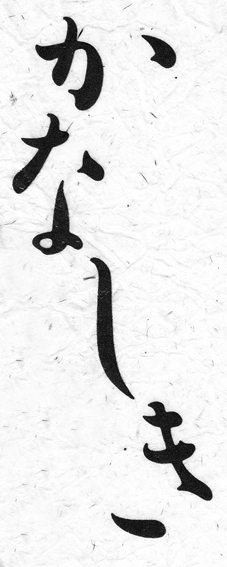
良寛
タイトルを聞くからにいかにも率直で脱力したエッセイ集である。
薄墨紙を思わせるグレーの表紙。その題字につかわれていた朱色の文字に、目が釘づけになった。
この本のことはなぜかいまでも覚えているのだが、改めて考えてみれば、かなの部分は「へ」と「な」の二つしかない、ということに気づいて愕然としてしまう。
その存在感は、きっと、不可思議な歪みのせいだ。
一見不揃いのようで、みる者を惑わせる微妙なずれ。そのくせじっと眺めていると、哀しげな表情から温もりが伝わってきて心が安らぐ。
このあやしくておもしろいかな書体は〈良寛〉という名前で、ほんとうに、あの良寛の筆跡からつくられたものだという。
幼少のころから和歌に親しみ、優れた詩人であった禅僧の良寛だが、書家としても有名で、古い名筆と呼ばれる書が残っている。
私にとって、良寛は、手毬をついて子どもたちと遊んでいる江戸時代のお坊さん、いわゆる「良寛さん」のイメージだ。いばったことが大嫌いで、子どもを愛し、「高名な人物からの書の依頼は断っても、子どもたちから凧に文字をかいてほしいと頼まれたときには喜んでかいた」という微笑ましいエピソードも、庶民派の良寛らしい。
この私が良寛の書について語るのは恐れ多いことのように思えるけれど(何しろ私が良寛の字を知ったのは本物より写植書体の〈良寛〉の方が先なのだ)、その筆がいかに型破りであったかは誰にでも一目瞭然だ。
いまにも力尽きて、消え入りそうな、寂寥感の漂う細い線。お世辞にも達筆とはいいがたい。
子どものころ、火をみるのが好きだった。
「オール電化」などという言葉がまだめずらしかった時代ではあったにせよ、私は家事手伝いをろくにしない子どもだったので、火は身近なものというより、興味深い観察対象に近かった。バースデーケーキに立てられた蝋燭も、アラジンストーヴの青白い炎も、クリスマスのキャンドルも。
とくにおもしろいと思ったのは、自分の身のまわりにある目に見えない空気は、意外なほど活発に動いている、ということだった。じっと息をつめているつもりでも、隣の部屋のドアや、ひとの気配で、火のかたちは脈をうつようにゆらめき、重心がどこにあるのか判然としない。
何とか焦点をあわせようとしているうちに、なぜか自分の身体が妙に生々しく感じられたものだ。
写植書体の〈良寛〉が世に出たのは1984年。良寛の筆跡から印刷用書体の文字板をつくるという大それた試みが実現した理由について、設計者の味岡伸太郎氏は、「自分がタイポグラフィの素人であったことだ」と、述べている。
多くのひとの目にふれる書体をつくりたい、とか、文字は万能でなければならない、とか、タブーや要求が一切ない場所にいたからできたことだ、と。
良寛というひとも、本来の書家ではなかったからこそ、もしかして同じようなことを考えていたのではないか。「書道」という大きな流れではなく、目の前の小さいものを照らすようにして、こんな文字をかいたのではないか。
でもそれは、どんなに孤独で、情熱と精神力を要することだったろう。
この書体に宿った面影は、いまも私を惹きつけてやまない。
世の不均衡に耐えながら、焦がれるように、何かを祈っている。そのような文字にみえる。